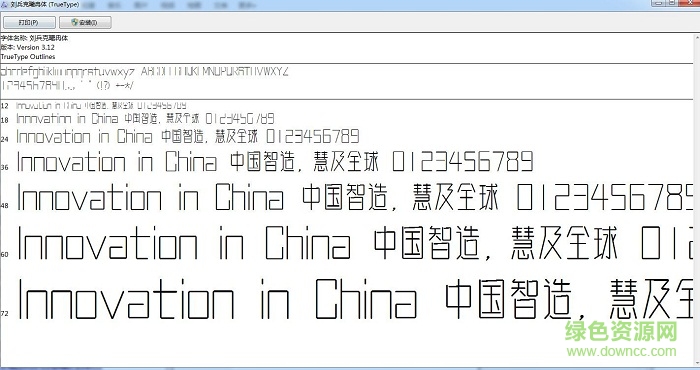
劉兵克曦冉體合集包含了常規(guī)版和超細(xì)版兩款字體,線條纖細(xì)干凈,整體設(shè)計有創(chuàng)意,用作美術(shù)字體非常棒,但是辨識度較低,不適合用于排版印刷,有需要者歡迎免費下載!
這是一款設(shè)計優(yōu)美,風(fēng)格簡約的美術(shù)字字庫,字形修長,特點鮮明,適用于各類時尚品牌的廣告設(shè)計與包裝。
字體優(yōu)美清新,線條流暢,給人以華麗柔美之感,此種類型的字體,適用于女用化妝品、飾品、日常生活用品、服務(wù)業(yè)等主題。